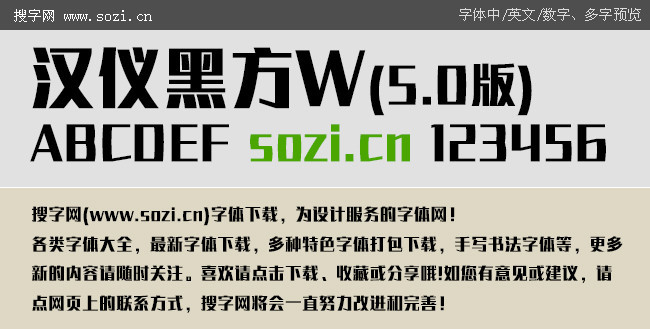
漢儀黑方5.0
搜字網(wǎng)提供一款漢儀黑方5.0中文字體下載,漢儀黑方非常方正,筆畫(huà)也很粗,很有黑體的特色,而且重心較高,看起來(lái)也比較高挑,向下書(shū)寫(xiě)的筆畫(huà)略微增加了一些弧度,讓字體看起來(lái)不是那么死板,也增加了一些個(gè)性,能夠適用于藝術(shù)設(shè)計(jì)、包裝印刷、海報(bào)設(shè)計(jì)、圖形設(shè)計(jì)等領(lǐng)域。(如需要商用請(qǐng)聯(lián)系漢儀字庫(kù)購(gòu)買(mǎi)版權(quán))